Hebräisch
Die hebräische Schrift gehört zu den ältesten lebendigen Schriftsystemen der Welt. Aus dem phönizischen Alphabet hervorgegangen, von rechts nach links gelesen und bis heute in religiösen Texten, im modernen Iwrit und in Kunst und Wissenschaft tief verwurzelt.
Heilige Zeichen
Vom Konsonanten zum Alphabet
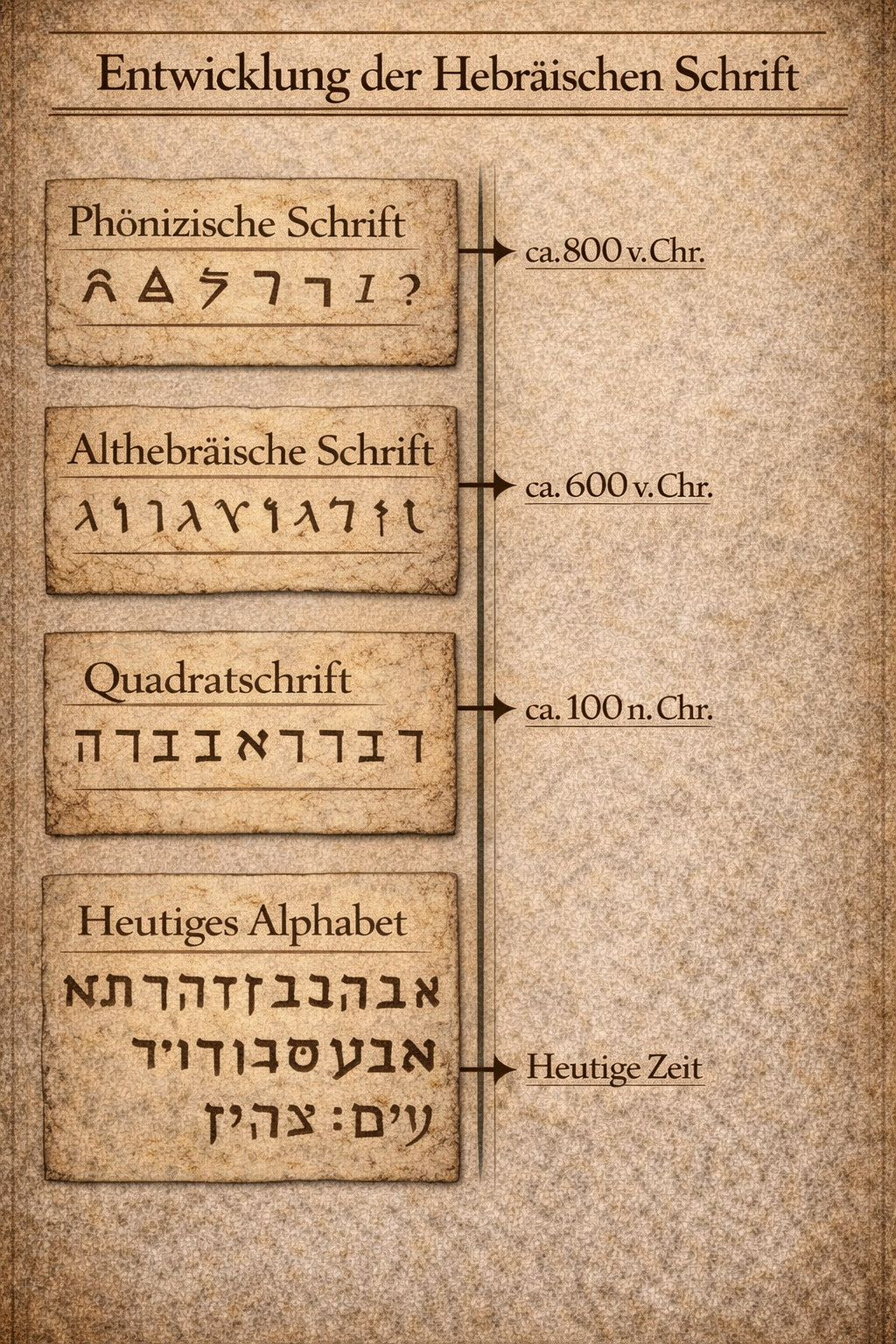
Ab 1000 v. Chr.
22 Buchstaben — eine Welt
Das hebräische Alphabet kennt nur Konsonanten, Vokale werden durch Punkte angedeutet. So bewahrte es über Jahrhunderte die Worte der Tora und wurde zum Träger einer ganzen religiösen und literarischen Tradition — vom Schriftrollen-Skriptorium bis ins heutige Israel.